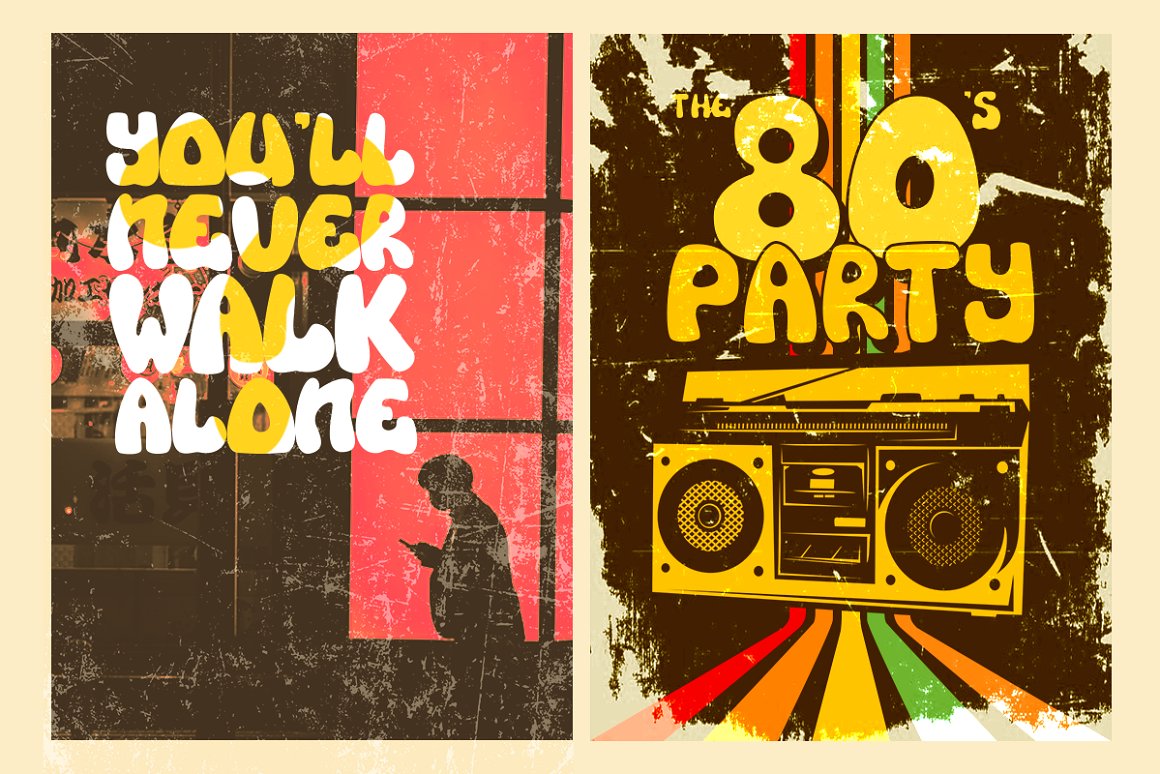
Various – Y2K Display Font
Dites bonjour à DIVERS ! Police complètement unique et personnalisée avec un style années 00, inspirée des panneaux rétro vintage et peints à la main
Divers est une police avec une délicieuse touche rétro, parfaite pour capturer l’essence des designs des années 60, 70, 80, 90 et même de l’an 2000 ! Ses caractéristiques uniques vous transporteront dans ces époques emblématiques, ajoutant une touche nostalgique à vos projets créatifs.
Divers est disponible en deux versions – Regular et Outline. Avec deux polices de styles différents, vous pouvez facilement créer des designs accrocheurs sans aucun effort supplémentaire
Cette police est parfaite pour un thème rétro des années 2000 et peut être utilisée pour les magazines de couverture, les brochures, les logos, les titres ou les citations, les affichages autonomes et les courts paragraphes ou contenus. Chaque police de la famille est dynamique et fait autorité, ce qui la rend parfaite pour tout projet d’affichage.
suppléants et ligatures
Prise en charge multilingue